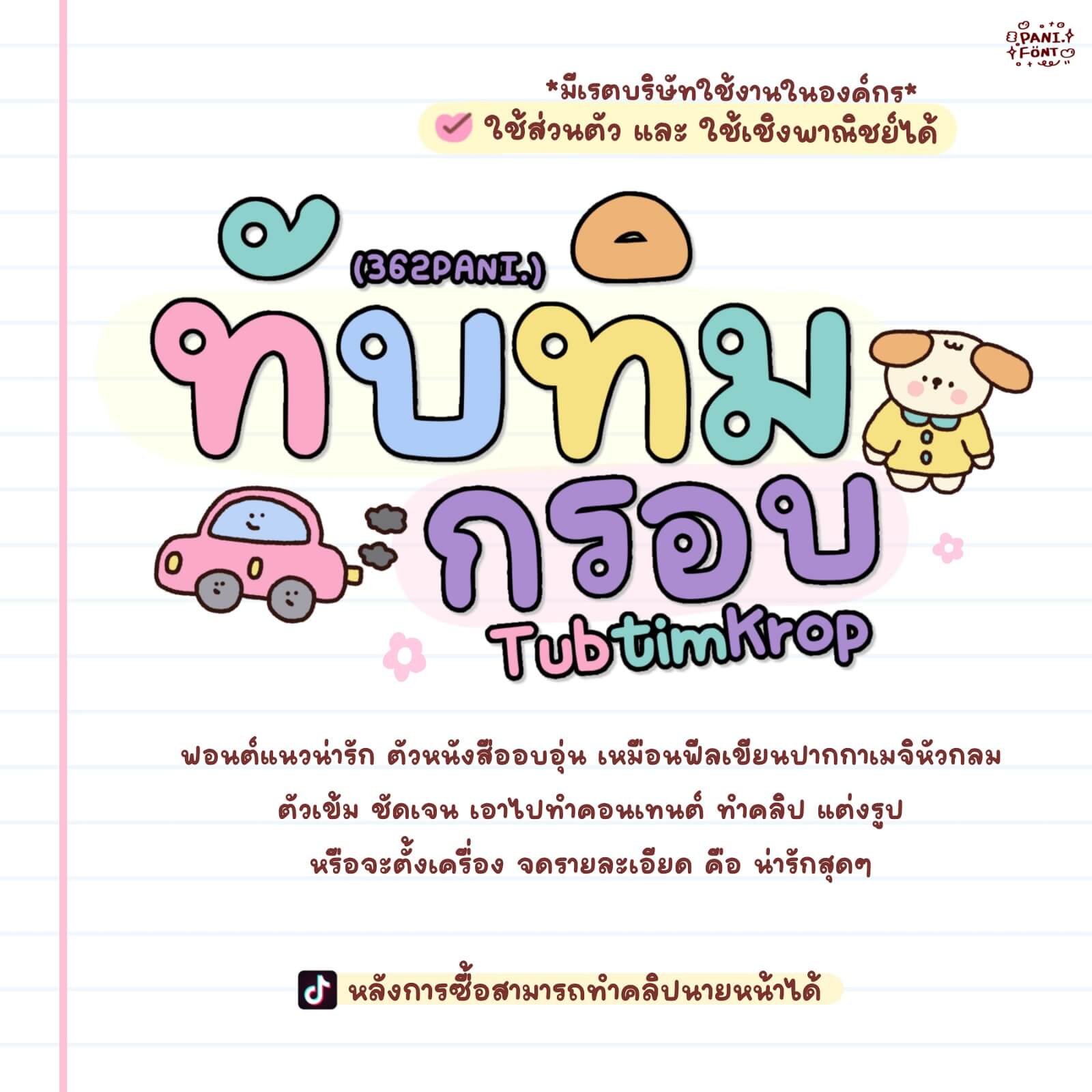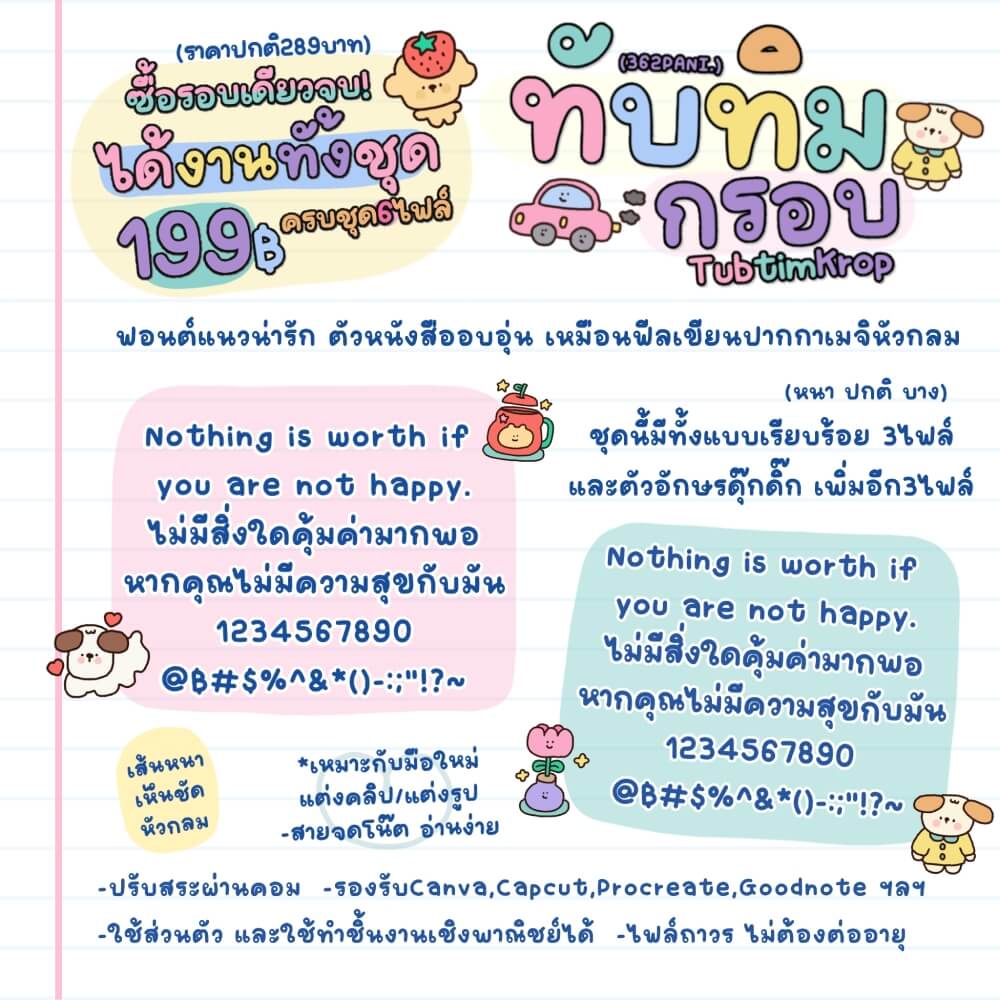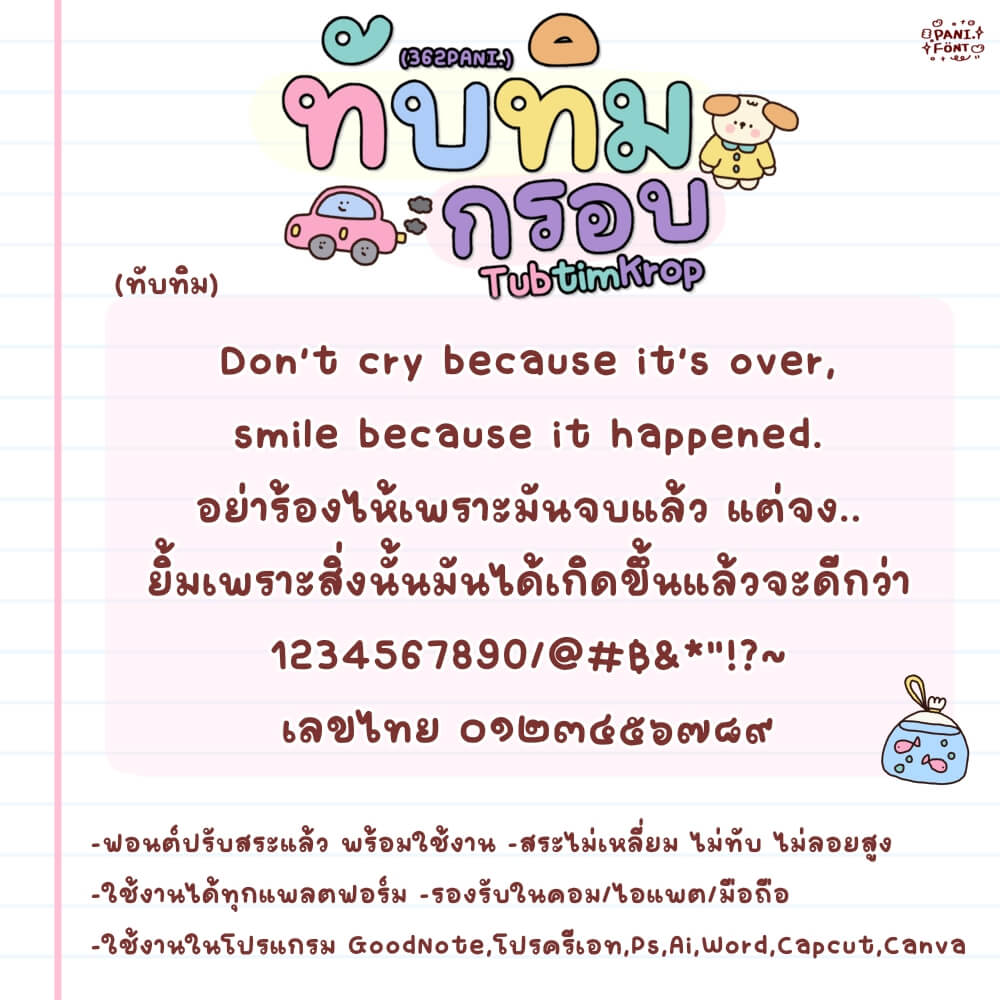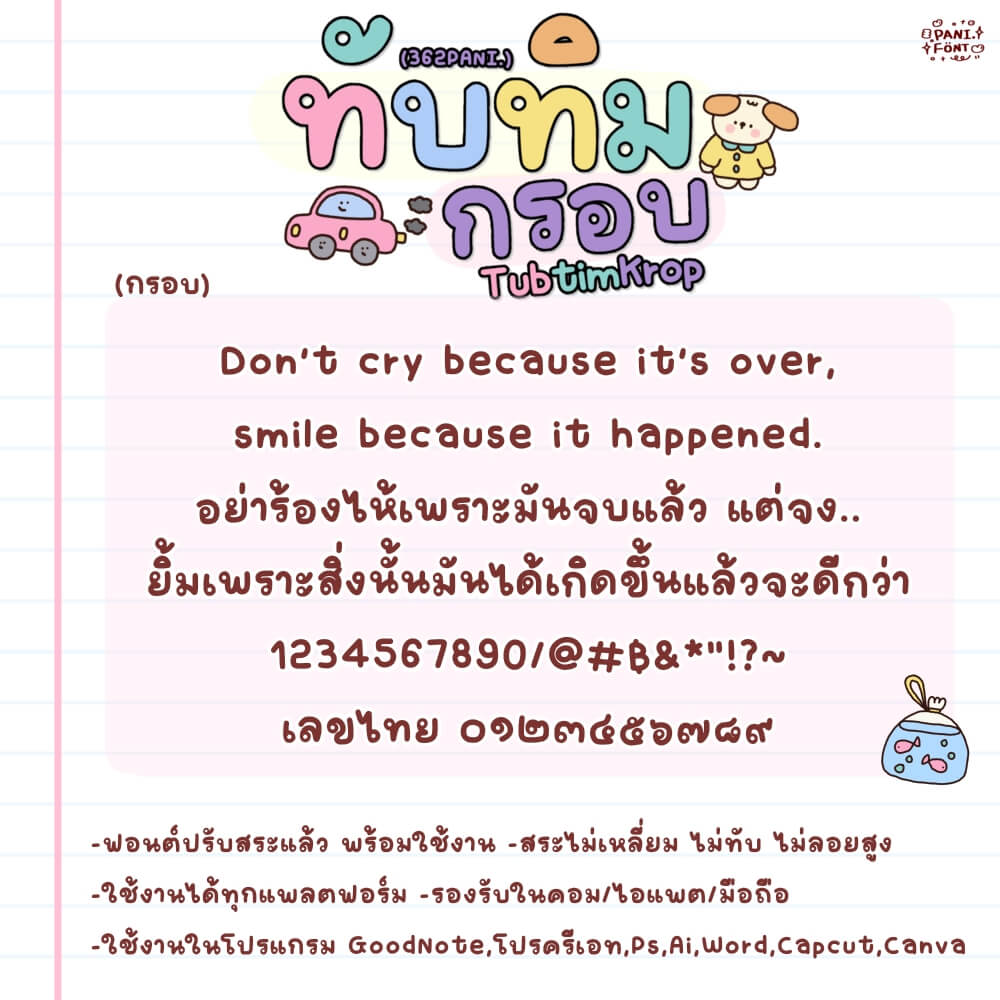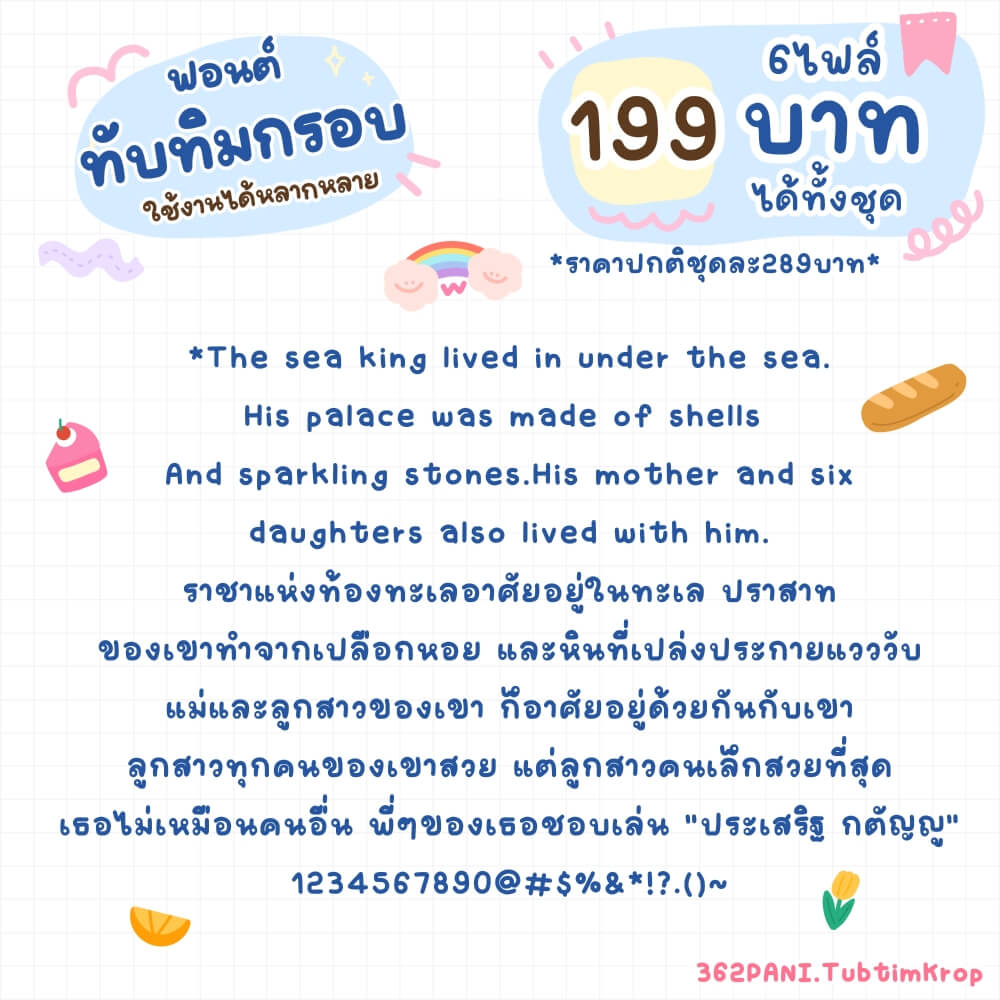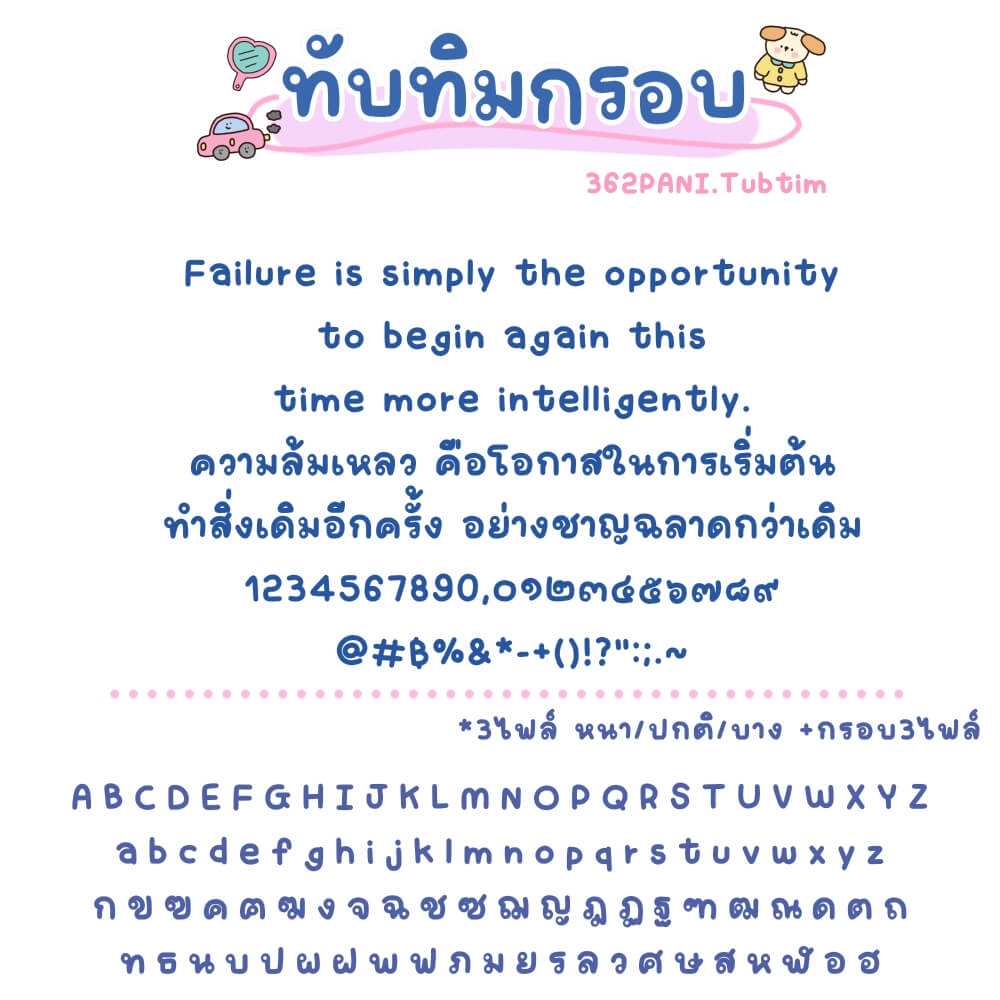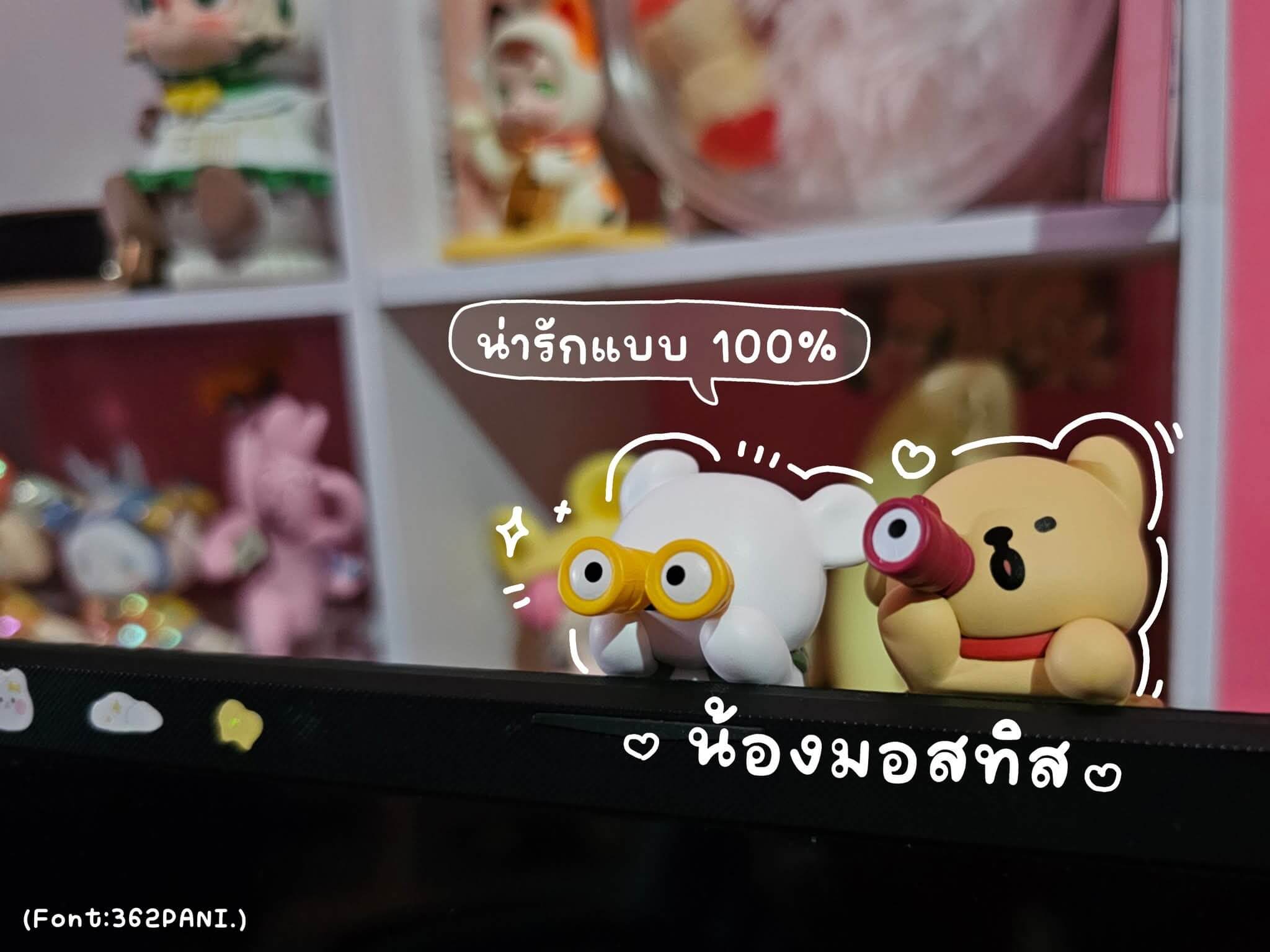
ฟอนต์ 362PANI.ทับทิมกรอบ – ฟอนต์แนวน่ารัก ตัวหนังสืออบอุ่น เหมือนฟีลเขียนปากกาเมจิกหัวกลม ตัวเข้ม ชัดเจน เอาไปทำคอนเทนต์ ทำคลิป แต่งรูป หรือจะตั้งเครื่อง จดรายละเอียด คือ น่ารักสุดๆ
362PANI.ทับทิมกรอบ